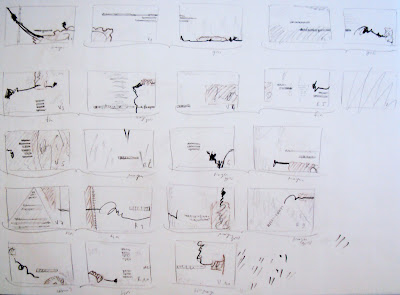
En avril, j'ai participé au stage que proposait Arlette. Chaque année, deux stages sont organisés par Liliane Buchi : celui de novembre dernier étant complet, je n'ai pas pu l'intégrer mais ce n'est que partie remise... En juin, chez Apex, elle nous fera travailler sur les mêmes éléments !
Nous devions apporter du carton d'emballage de faible épaisseur, de grande feuille de couleur (épaisse de 250 g à 300 g), des papiers asiatiques, différents papiers (en lien avec la chanson de Régine), des acryliques, des gouaches, de l'encre de Chine... un outil scripteur issu de la nature en plus de tout notre bazar pour la calligraphie.
Nous avons d'abord travailler les traces avec 6 outils de formes et tailles différentes dont l'outil issu de la nature. Cela nous a permis de nous décrasser et de libérer nos gestes.
Arlette nous a demandé de choisir deux couleurs ; pour moi, ce sera : Indigo et Raw Sienna > marque Fevicryl (trouvée chez Centrakor suite au stage avec Edwige Timmerman), auxquelles j'ai aussi ajouté du Terracota et Silver par petites touches.
Nous avons réalisé des monotypes sur différents papier asiatiques qui seront utilisés plus tard sous forme de collage.
Arlette nous a laissé la possibilité de travailler sous forme de page pour former un livret ou pour faire un mobile... Je suis partie sur l'idée du livret même si maintenant que toutes les pages sont finalisées, je me rends compte que je n'avais pas trop réfléchi à la reliure lors de ma mise en page !
Les dimensions de mes pages sont : 18 x 11 cm. J'ai utilisé deux épaisseurs différentes de carton. J'ai 10 cartons en tout > soit 20 pages (recto-verso).
Nous avons enduit (plus ou moins) nos pages avec de l'acrylique avec un rouleau mousse (de peintre).
Puis, il fallait commencer à réfléchir à l'organisation des pages entre elles pour ensuite s'attaquer à la composition...
Arlette nous a demandé de faire un chemin de fer afin de poser sous forme de croquis nos idées et nous permettre d'avoir une trame toujours à portée de main lors de la réalisation des pages.
| effet du fond au crayon de papier, traces en noir, collages en sanguine, lignes de texte à la mine de plomb |
Lorsque les fonds ont été secs, j'ai collé mes différents papiers monotypés puis fait mes traces.
Sur la liste pour la préparation de ce stage, Arlette avait choisi un symbole pour définir les 2 couleurs qui seraient utilisées en acrylique, en gouache, en papier...
Ce symbole était celui de l'infini.
Je l'ai interprété comme un élément à prendre aussi en compte et j'ai donc cherché un texte en rapport... J'ai choisi " Les deux infinis " de Blaise Pascal (1670). Au vu de la longueur du texte et de ce que je pouvais réellement écrire sur mes pages, j'ai sélectionné quelques passages qui ont été calligraphiés en humanistique à la plume fine en gouache noire.
Pour une fois, j'ai réussi à finir mon livret durant le stage... Les autres propositions d'Arlette (leporello, mobile et autres...) seront peut-être réalisés plus tard...
| 1e de couverture |
| 4e de couverture |